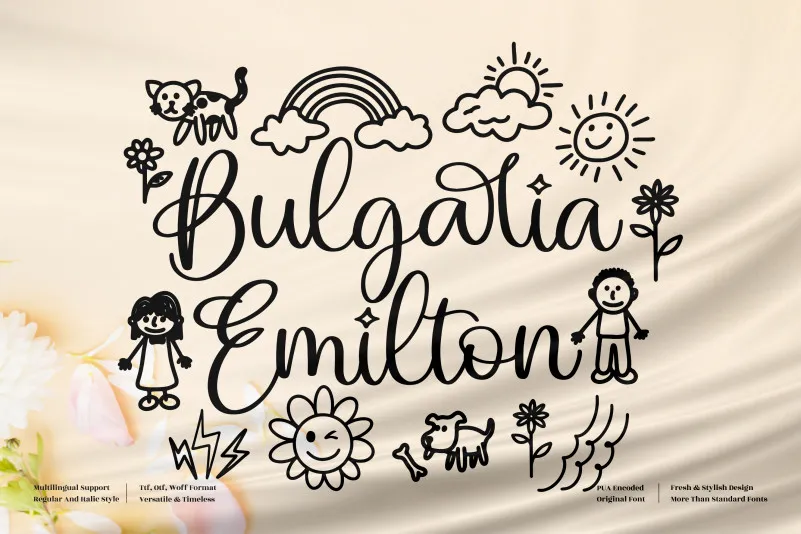
Bulgaria Emilton Font – Download Grátis
A Bulgária Emlinton Font é uma elegante tipografia script que surgiu do talentoso Perspectype Studio. Seus traços delicados e fluidos se destacam como a escolha perfeita para qualquer projeto, desde criações de marca, decoração de produtos até designs gráficos pessoais e embalagens. Suas formas românticas são ideais para logos e cartões de visita, capas de livros e materiais promocionais que exigem uma pitada de sofisticação. Com sua facilidade na aplicação em diversas mídias digitais e físicas, esta fonte é um recurso indispensável para quem busca criar obras impecáveis e cheias de estilo. É a escolha certa se você está buscando trazer a elegância do script à sua próxima criação gráfica.